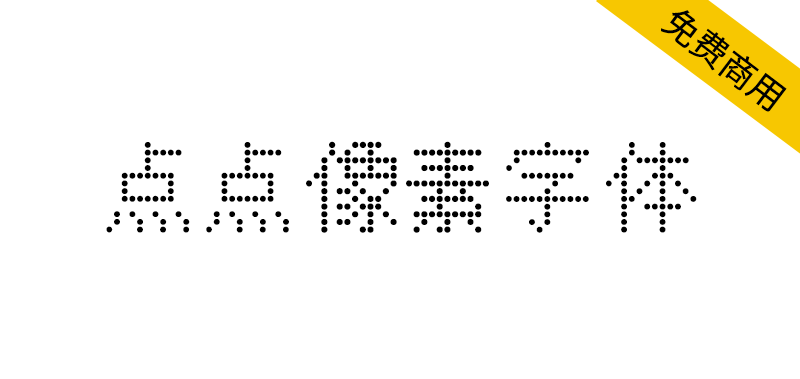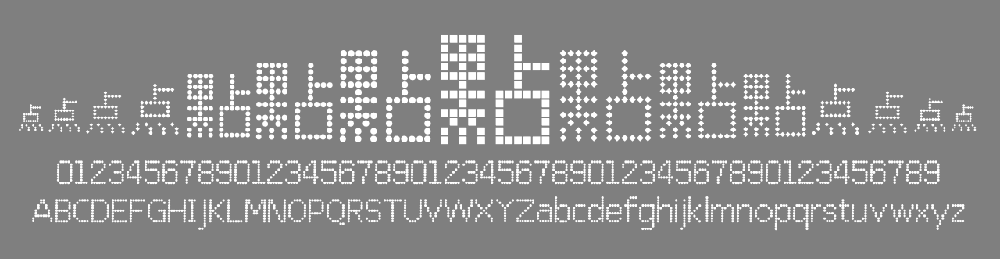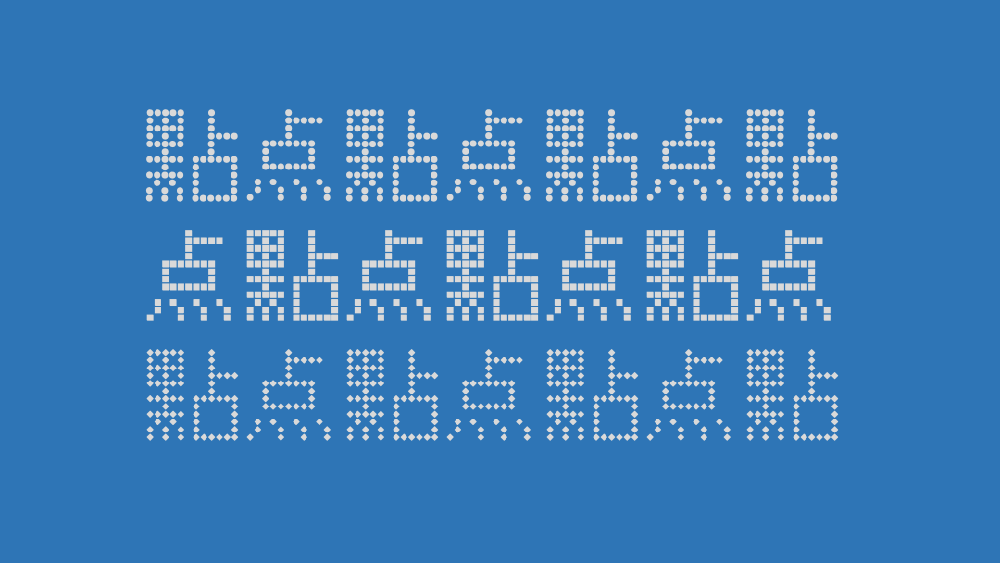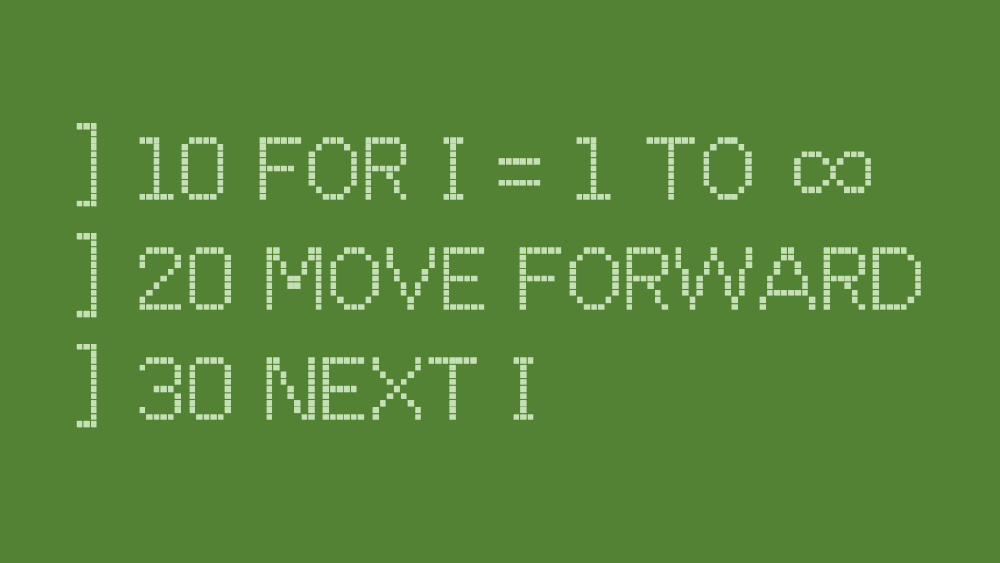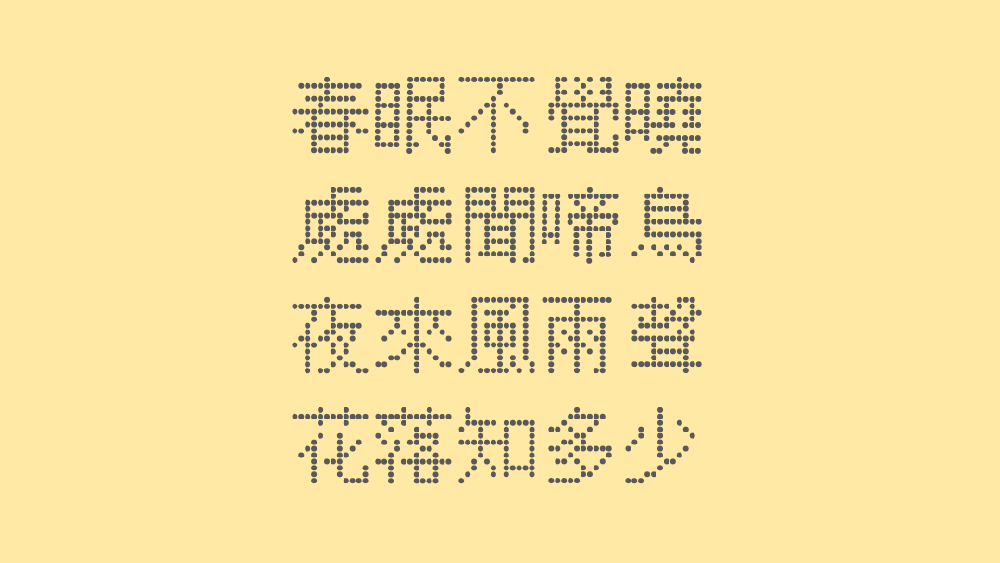
点点像素字体是一个在GPL 2.0协议下免费开源发布的,涵盖超过22000字形的大字符集中文像素艺术字体。基于同样以GPL 2.0协议开源的自由字体「文泉驿点阵宋体」,经自动矢量化转换,变形和美化得到的。点点像素字体使用的将点阵字体自动转换为OpenType字体的源代码也已开源。
目前可见的中文像素艺术字体大多有商业许可协议保护,且很多无法涵盖GBK字符集中的全部汉字字形。点点像素字体及其转换工具提供了从开源点阵字体生成开源像素艺术字体的另一种可能。